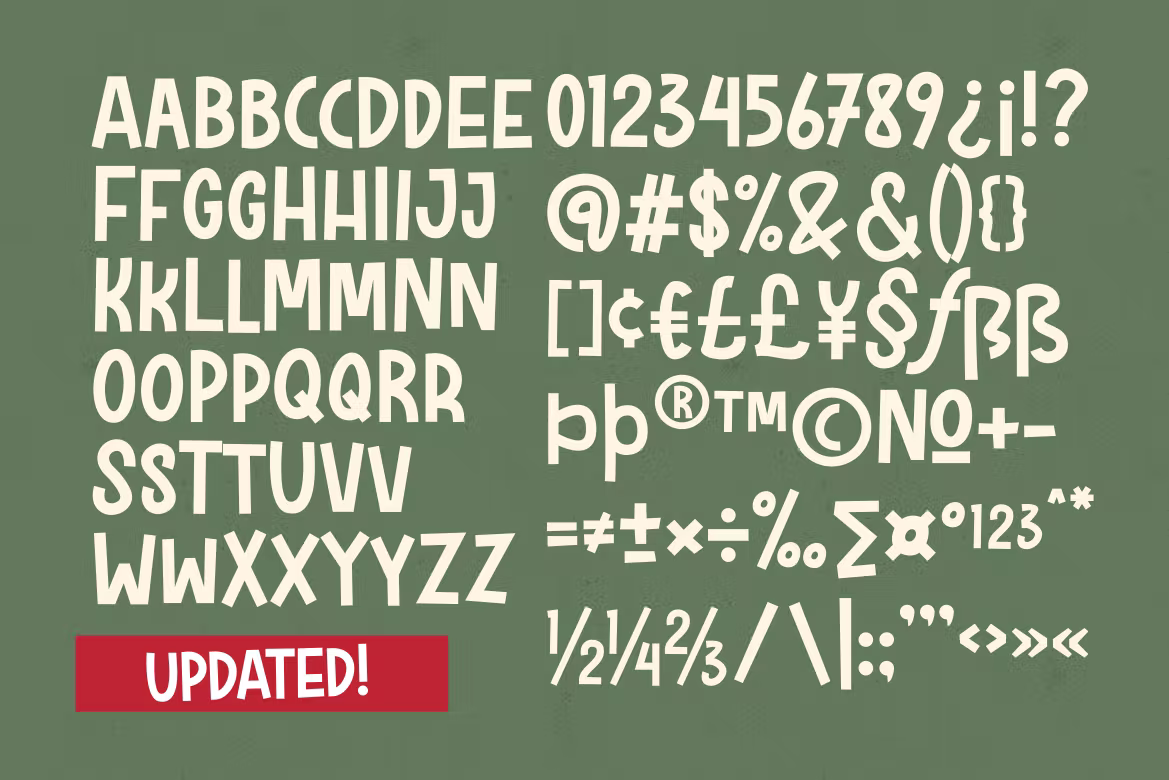
Rockinsoda Font
Description de Rockinsoda Font
La police Rockinsoda est une police d’affichage avec un style d’écriture manuscrite d’enfant avec peu d’improvisation sur le mode majuscule, bien que ces polices soient toutes des polices majuscules. Cette police comporte également des lettres minuscules alternatives qui peuvent être utilisées pour la dernière lettre ou la couverture du mot. Cette police est parfaite pour tout ce qui concerne la nourriture, les enfants, les illustrations pour enfants, les titres de livres, le titre de sites Web, l’écriture sur vidéo ou tout ce que vous pouvez essayer d’acquérir de l’expérience dans les besoins de conception graphique.